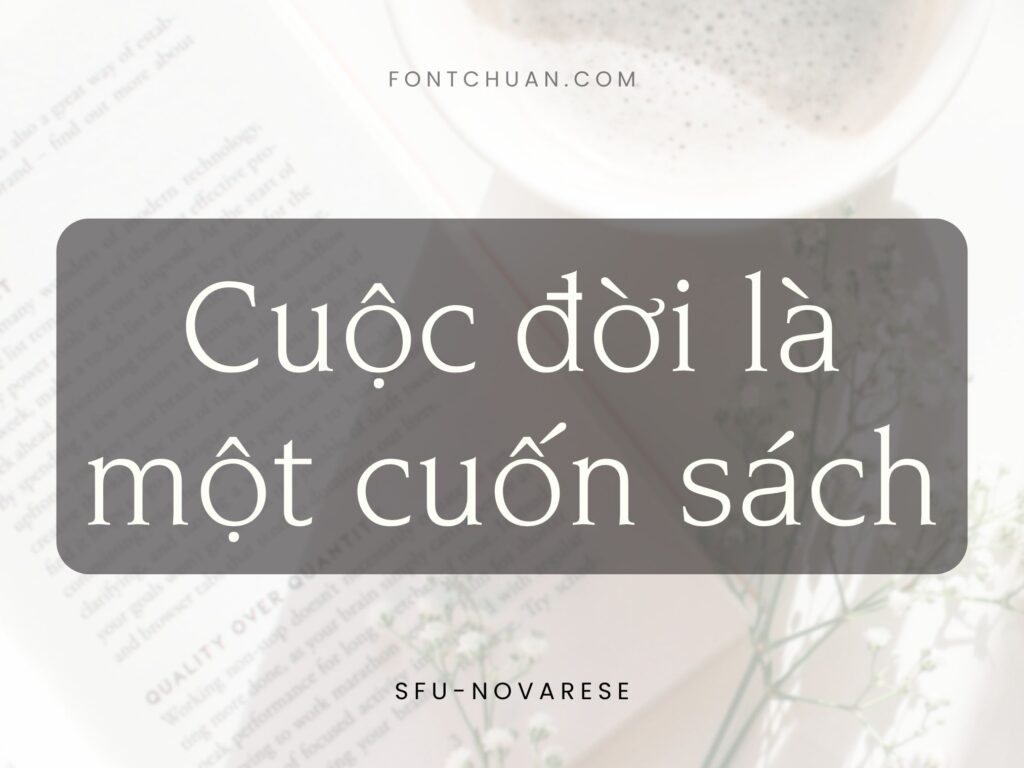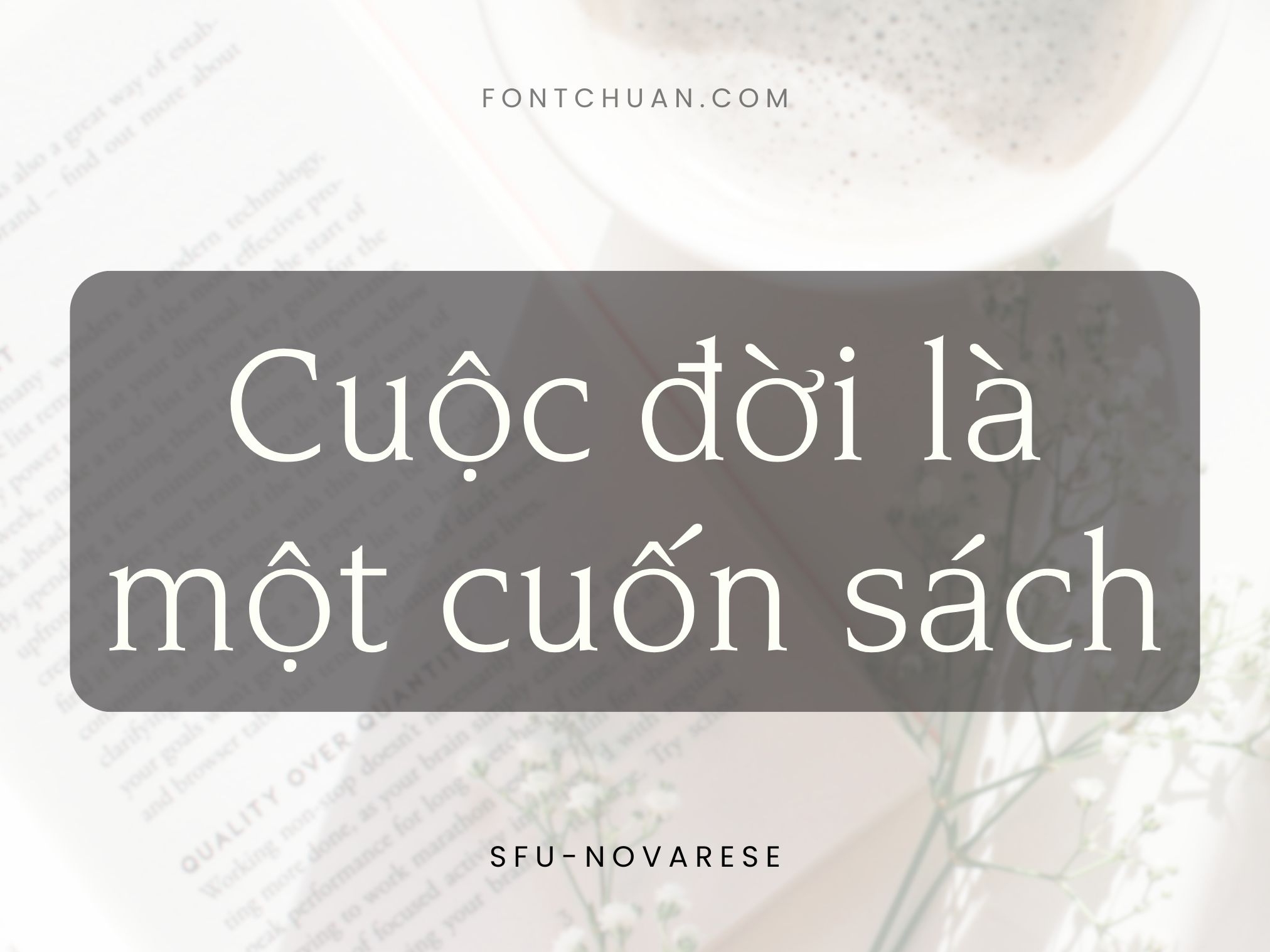
Novarese là một Font chữ quảng cáo thuộc nhóm serif, được thiết kế bởi Aldo Novarese và phát hành lần đầu tiên vào năm 1980. Font này mang phong cách cổ điển xen lẫn hiện đại, tạo nên sự sang trọng và chuyên nghiệp trong các ấn phẩm thiết kế. Novarese được sưu tầm và đăng bởi thành viên của Font Chuẩn, trở thành lựa chọn đáng tin cậy cho các nhà thiết kế muốn tìm kiếm một kiểu chữ vừa tinh tế vừa linh hoạt trong ứng dụng.
Về mặt thiết kế, Novarese có các đường nét thanh mảnh, tỷ lệ cân đối và độ tương phản cao, tạo cảm giác thanh lịch và dễ đọc. Font này hỗ trợ nhiều ngôn ngữ và bao gồm các ký tự đặc biệt, giúp người dùng dễ dàng tùy chỉnh theo nhu cầu. Bên cạnh các ứng dụng chuyên nghiệp như sách, tạp chí, nhận diện thương hiệu, Novarese cũng lý tưởng để thiết kế font chữ Tết, giúp tạo ra các thiệp chúc mừng năm mới, poster hay banner mang không khí lễ hội, vừa sang trọng vừa bắt mắt. Các ngành nghề như xuất bản, giáo dục và thiết kế đồ họa đều có thể tận dụng kiểu chữ này để tạo dấu ấn đặc biệt trong truyền thông.